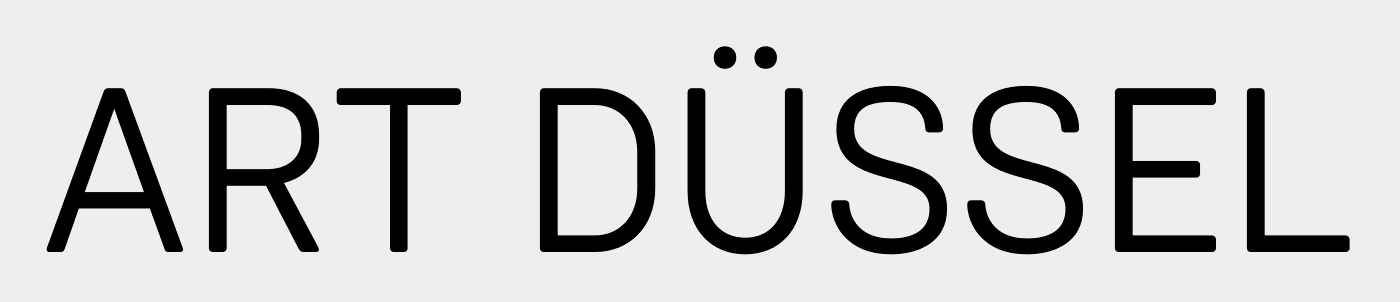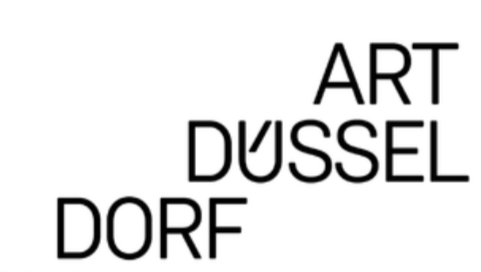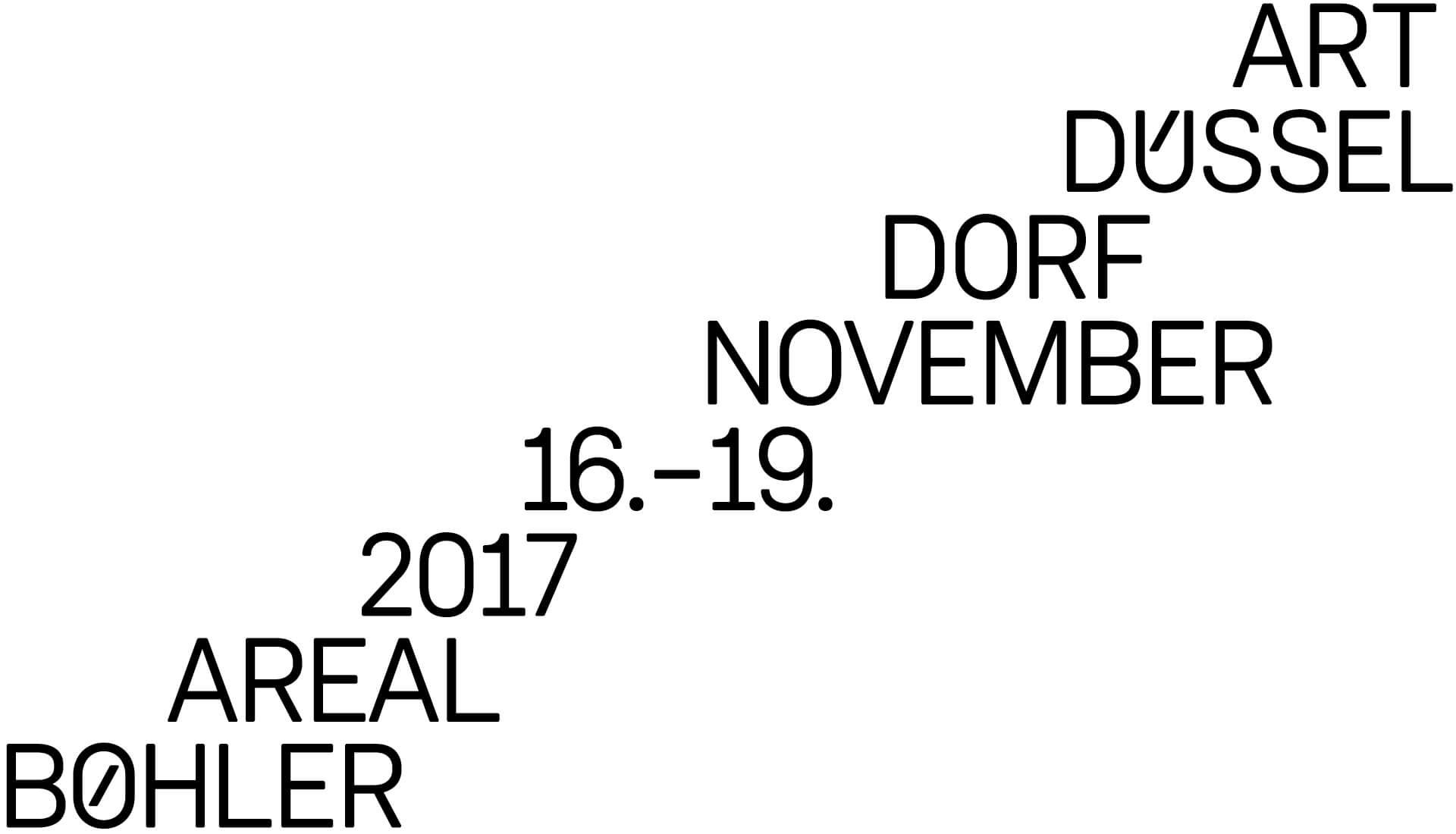
Suche Schrift von der "Art Düsseldorf" Nov. 2018
ich habe letztens das Plakat der "Art Düsseldorf  16.-18. Nov. 2018" gesehen und bin jetzt auf der Suche nach der Schrift. Ähnliche Schriftarten würden auch gehen, vorausgesetzt "ö,ü,ä" sind vom Prinzip ähnlich. Mir gefallen, dass die Umlaute mit einem Strich, statt mit Punkten (wie im Deutschen) gekennzeichnet sind. (wirkt so skandinavisch).
Die Strich-Umlaute finden sich nicht in dem Font, wurden wohl händisch angelegt.